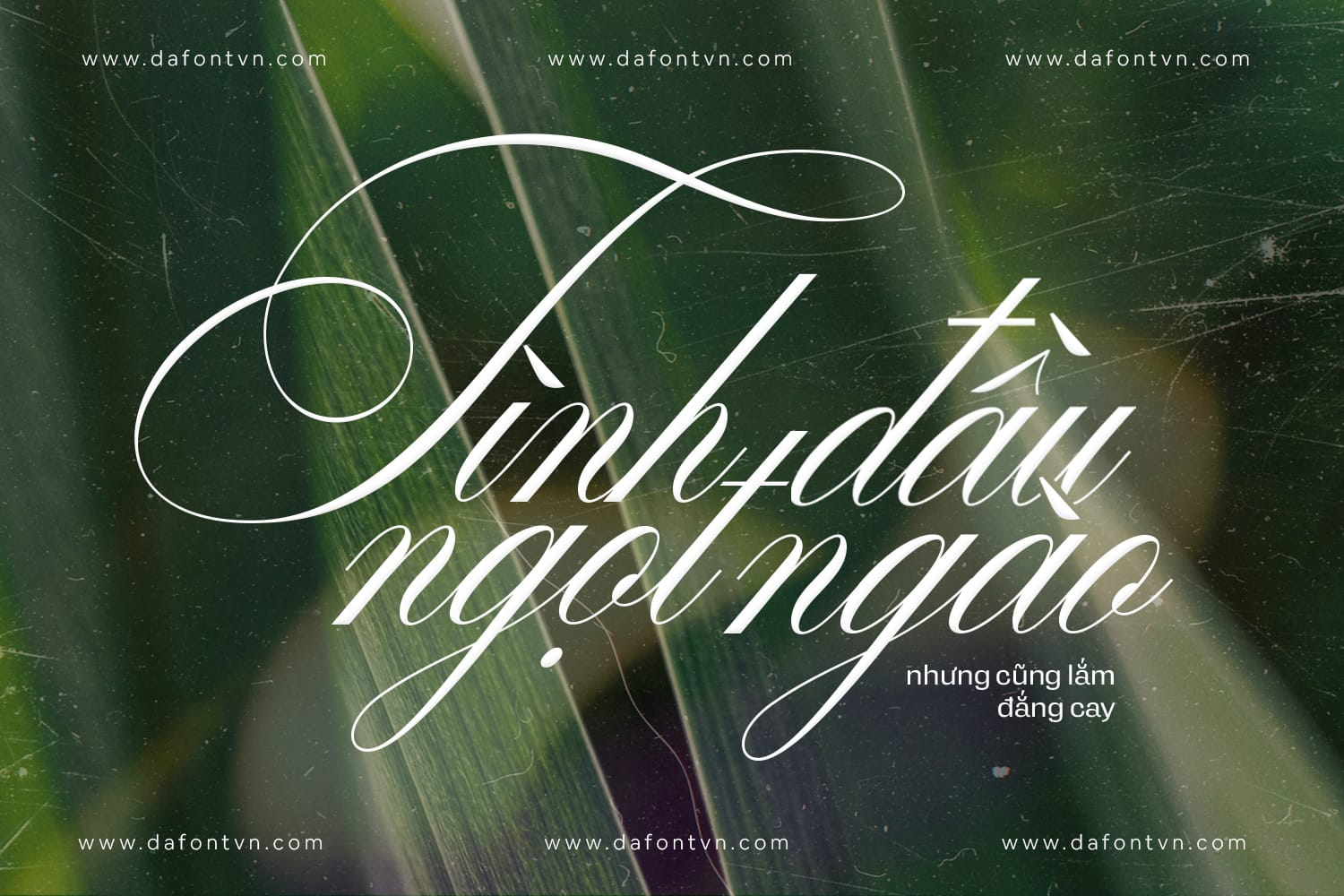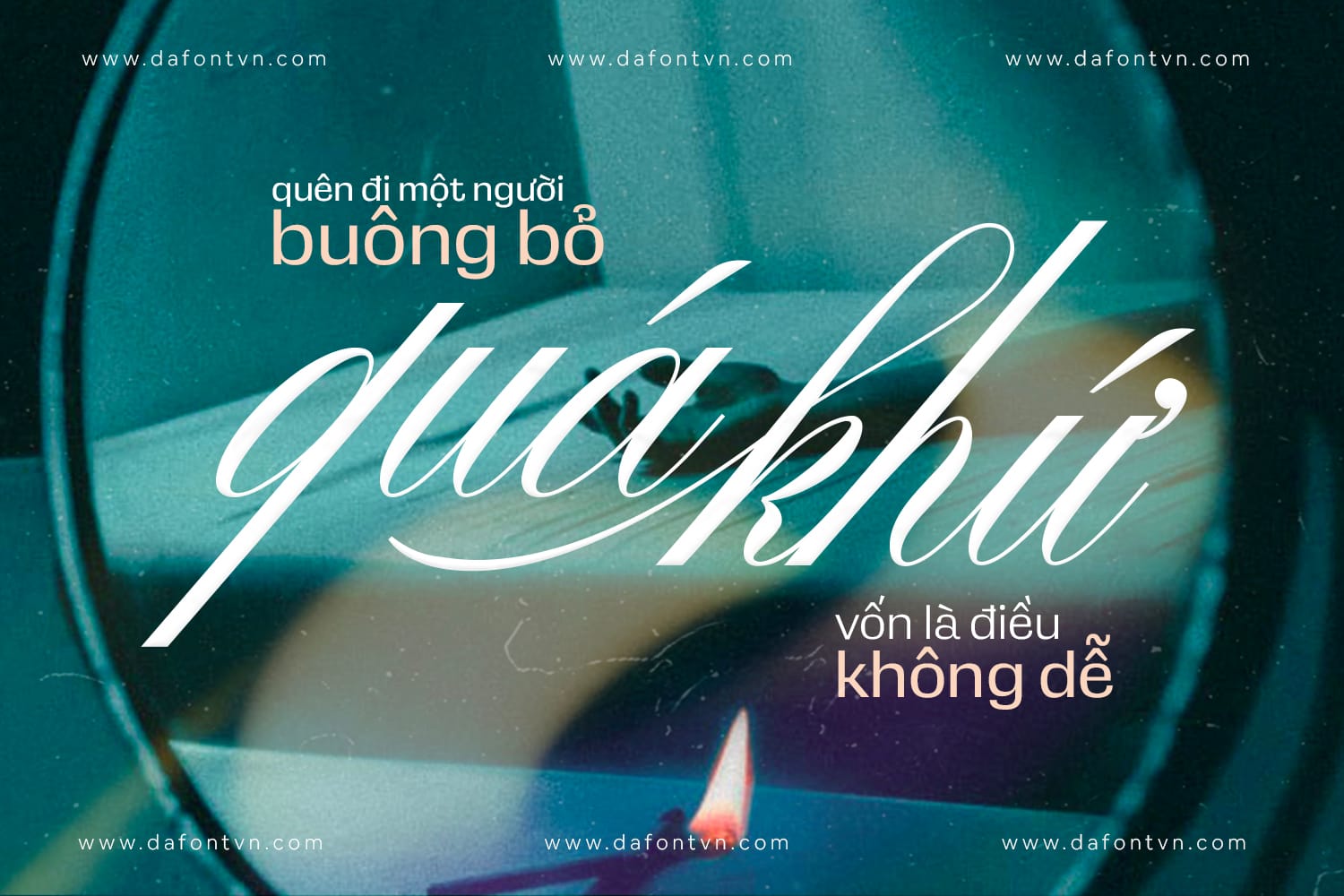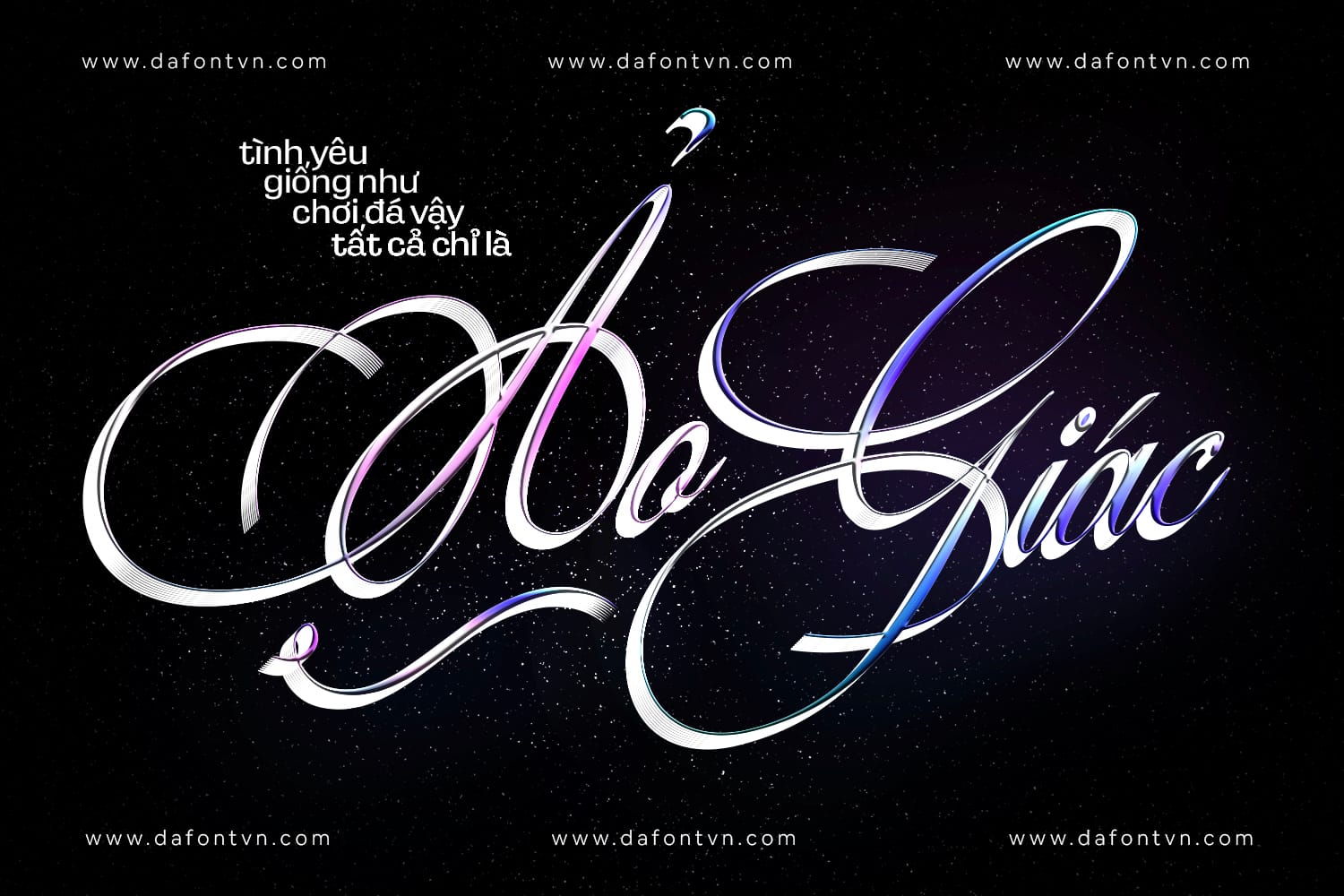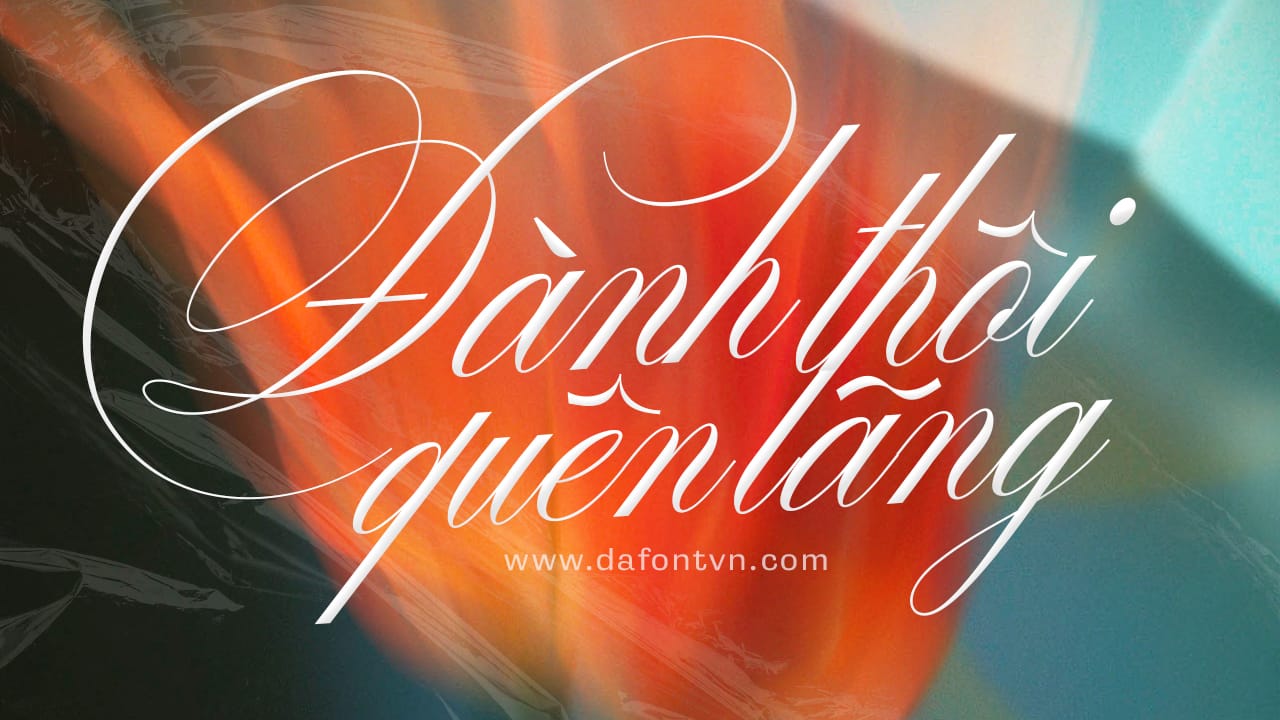
Desirable Calligraphy là một kiểu font thư pháp với phong cách cổ điển và một chút sang trọng, lấy cảm hứng từ chữ viết tay của phụ nữ Ý và các bản thảo cổ. Các nét chữ được thiết kế một cách cẩn thận và hài hòa với nhau khiến nó rất phù hợp cho rất nhiều thiết kế.
Font chữ rất này phù hợp cho các thiết kế như thiệp đám cưới, bìa sách, thiệp chúc mừng, logo, thương hiệu, danh thiếp, giấy chứng nhận hoặc bất kỳ thiết kế nào khác đòi hỏi sự cổ điển, trang trọng hoặc sang trọng.
Ngoài ra, font chữ còn bao gồm hơn 600 glyph chất lượng ở cả chữ hoa và chữ thường để bạn tha hồ sáng tạo cho ra các tác phẩm ấn tượng.
Đừng quên có một phiên bản textured khác của font này